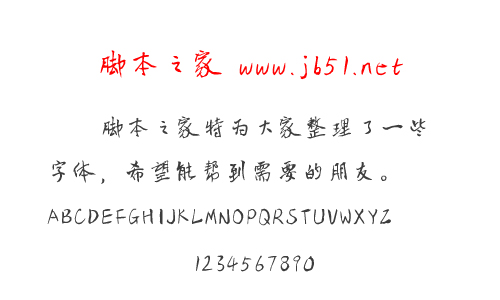
陳學(xué)儒毛筆書寫簡體字體是一款全新開發(fā)的中文字體,該字體線條粗細適中,筆畫柔韌老道,富有動勢,結(jié)體和暢優(yōu)美,氣息儒雅,整體效果出色,能夠適用于藝術(shù)設(shè)計、包裝印刷、簽名設(shè)計、圖形設(shè)計等領(lǐng)域,歡迎有喜歡或需要此字體的朋友們前來下載使用。